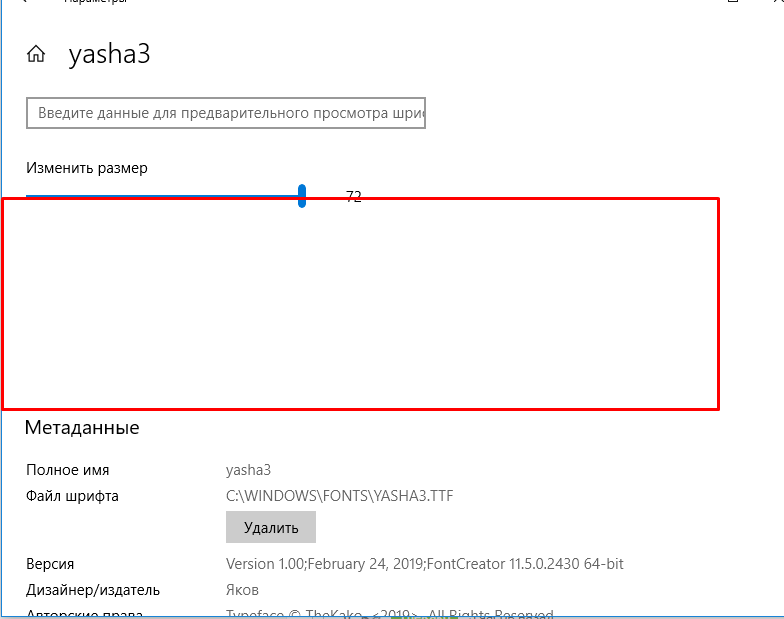
Шрифт из почерка.
Посидел я пару часиков, чутка почитал про функционал High-Logic FontCreator, посмотрел про лигатуры. Спасибо кстати вам)
И начал работать. Сейчас для примера строчных букв сделал предложения, а не отдельные экземпляры.
Составил,  работа пошла, упорно выделяя и редактируя каждую букву.
Результат получился таким:
Было видно что ещё не очень. Я продолжил.
Сейчас это меня вродь устраивает) Не думал даже что делать что-то подобное, может быть так занимательно, да и полезно.
Осталось реализовать программную составляющую для рандомных отступов, "плавающих букв" и т.д.
Я всегда думал, что у меня хреновый почерк... и вообще что я самый криворукий в этом смысле... :)